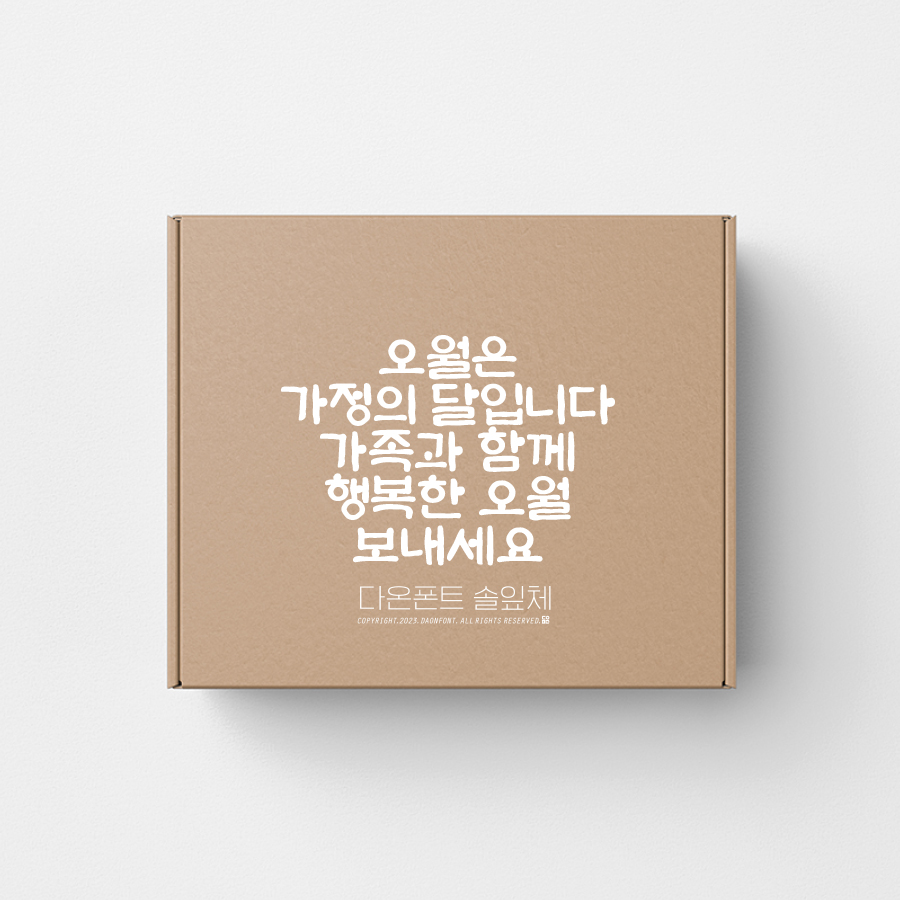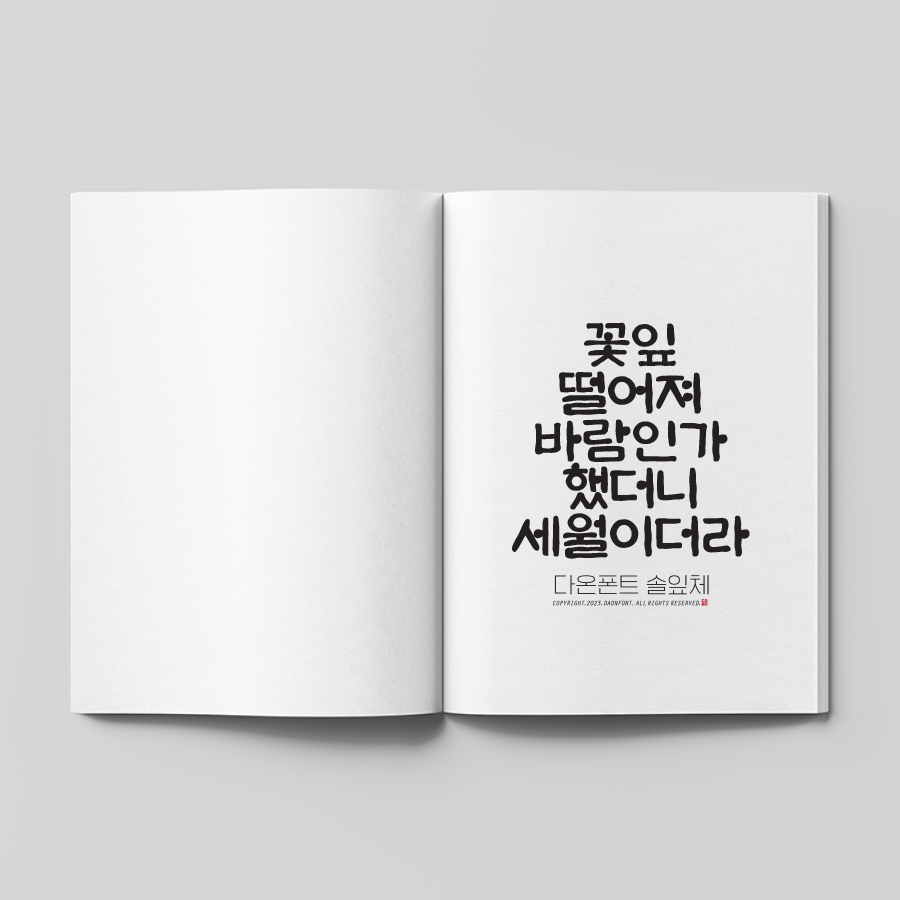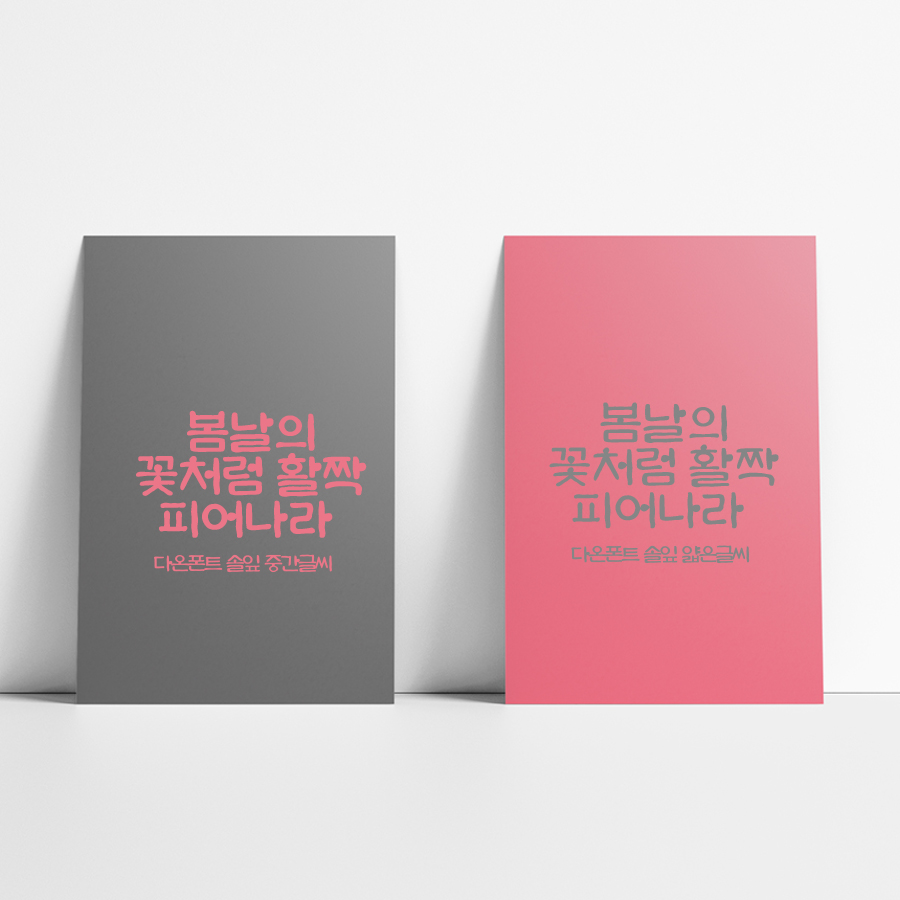
다온폰트 5월 첫 다온폰트 신서체, 다온폰트 솔잎체가 출시되었습니다.
먹향이 진한 붓글씨 서체인 솔잎체는 판본체를 기초로 제작된 서체입니다.
대문용 서체로 기획 제작되었으며, 한글 2780자와 영문, 숫자, 특수문자, 딩벳셋트로 구성되었습니다.
또한 자소에 굵기에 따라 2종 제작되었으니 상황에 맞게 사용하실 수 있습니다.